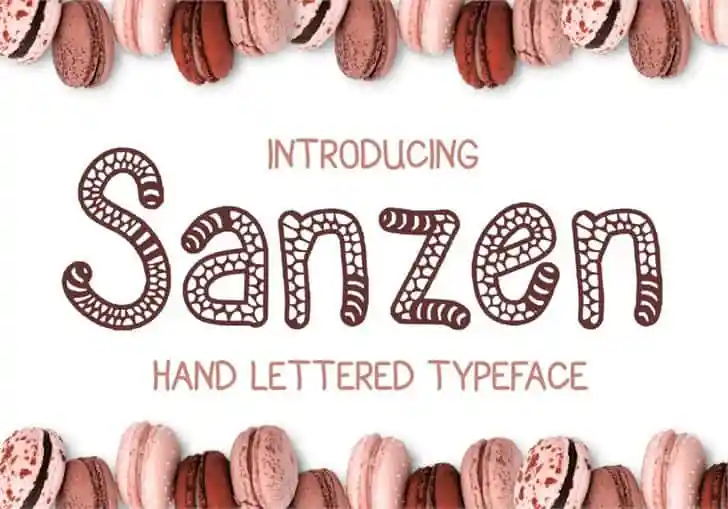
A Sanzen Font é uma tipografia de exibição que oferece um toque único para os designs mais criativos. Seu designer, Hamilton, criou este tipo de letra com uma paleta vibrante e expressiva que se destacará em qualquer projeto. A Sanzen está disponível para uso pessoal gratuito e comercial através do site Etsy, onde é possível adquirir licenciamentos comerciais completos. Esta fonte oferece um conjunto rico e diversificado de caracteres que complementa perfeitamente a sua personalidade vibrante. Seja você um designer digital, criador de arte ou artista gráfico, a Sanzen pode ser o ideal para tornar seus projetos mais memoráveis e impactantes.